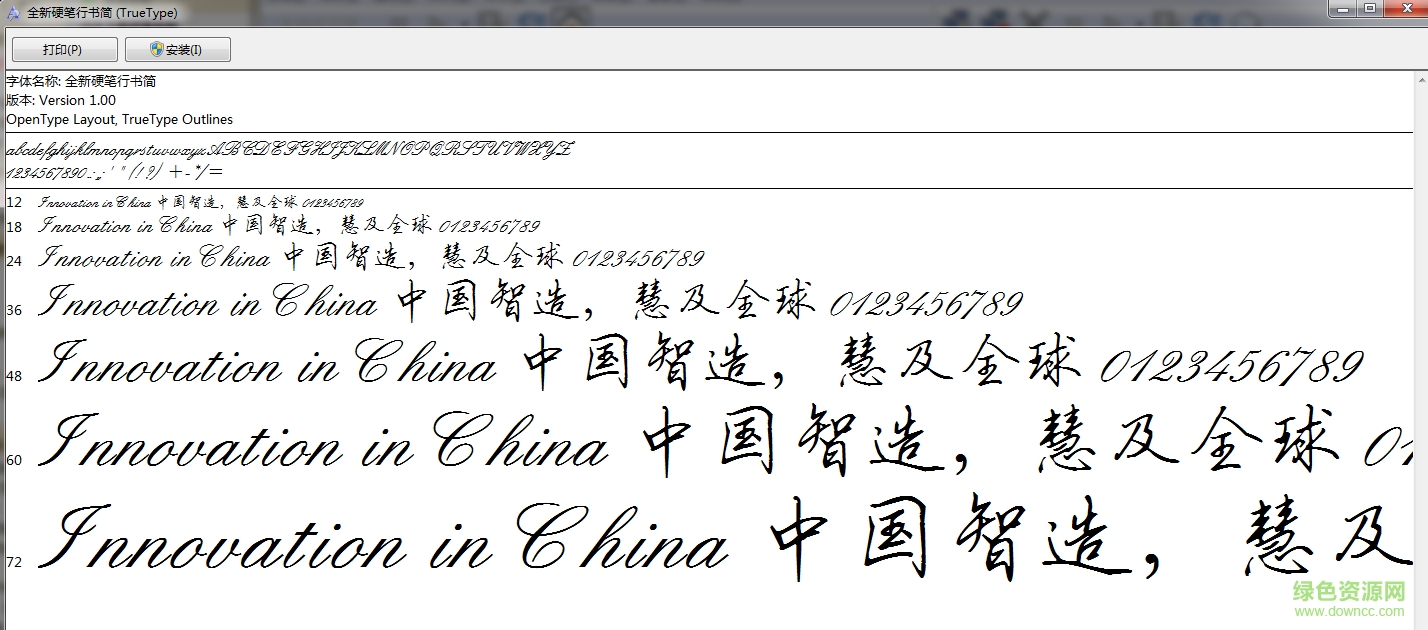
qxyingbixing是什么字體?qxyingbixing字體就是全新硬筆行書簡體,這款行書字體的結(jié)構(gòu)布局非常端正平穩(wěn),用筆不急不緩,韻意深長,大氣雅致,需要就來綠色資源網(wǎng)下載吧!
【上下貫穿】
貫穿行氣是行書布局謀篇的最重要的技巧。
【調(diào)整輕重】
“險(xiǎn)中求平”是造型藝術(shù)美的一個重要因素,而要取得平衡,必須學(xué)會調(diào)整輕重。
【力求和諧】
和諧主要包括一下幾點(diǎn):筆觸和諧統(tǒng)一、間白和諧統(tǒng)一、風(fēng)格和諧統(tǒng)一、字體和諧統(tǒng)一。